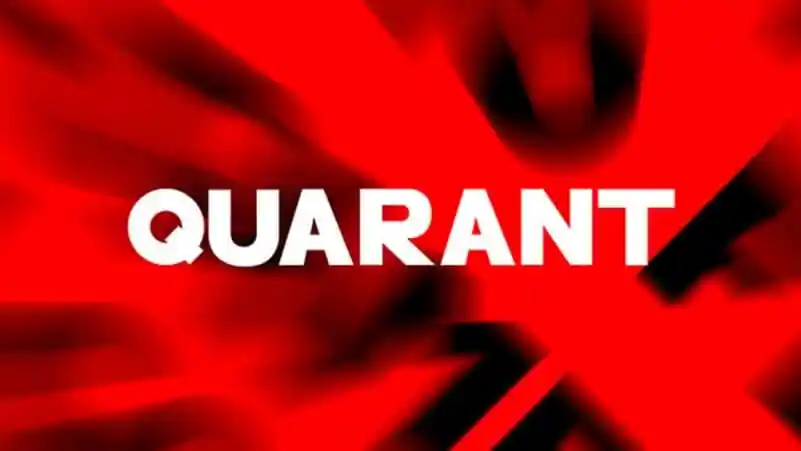
Descubra a atmosfera criativa e minimalista da Quarant Sans Serif Font, inspirada nos famosos logotipos modernistas. Especificamente projetada para desafios de design onde você precisa de uma fonte robusta e sólida que funcione perfeitamente tanto em títulos quanto em elementos visuais detalhados como motion graphics ou template design. Além disso, Quarant traz um toque autêntico da tipografia italiana moderna, oferecendo-lhe a oportunidade de criar designs para uma variedade de aplicativos desde brochuras e banners até vídeos e marcas. Seja você designer gráfico, publicitário ou criação de conteúdo digital, Quarant pode ser o recurso perfeito para suas necessidades em design. Com seu estilo único e sua robustez como fonte sem serif, Quarant é a escolha perfeita para aqueles que buscam uma tipografia versátil capaz de agregar um toque distinto às suas produções visuais. Este é o ideal para quem procura uma fonte robusta, elegante e moderna, perfeitamente adaptada para criar designs que vão além dos títulos simples, alcançando tudo em seu design gráfico.